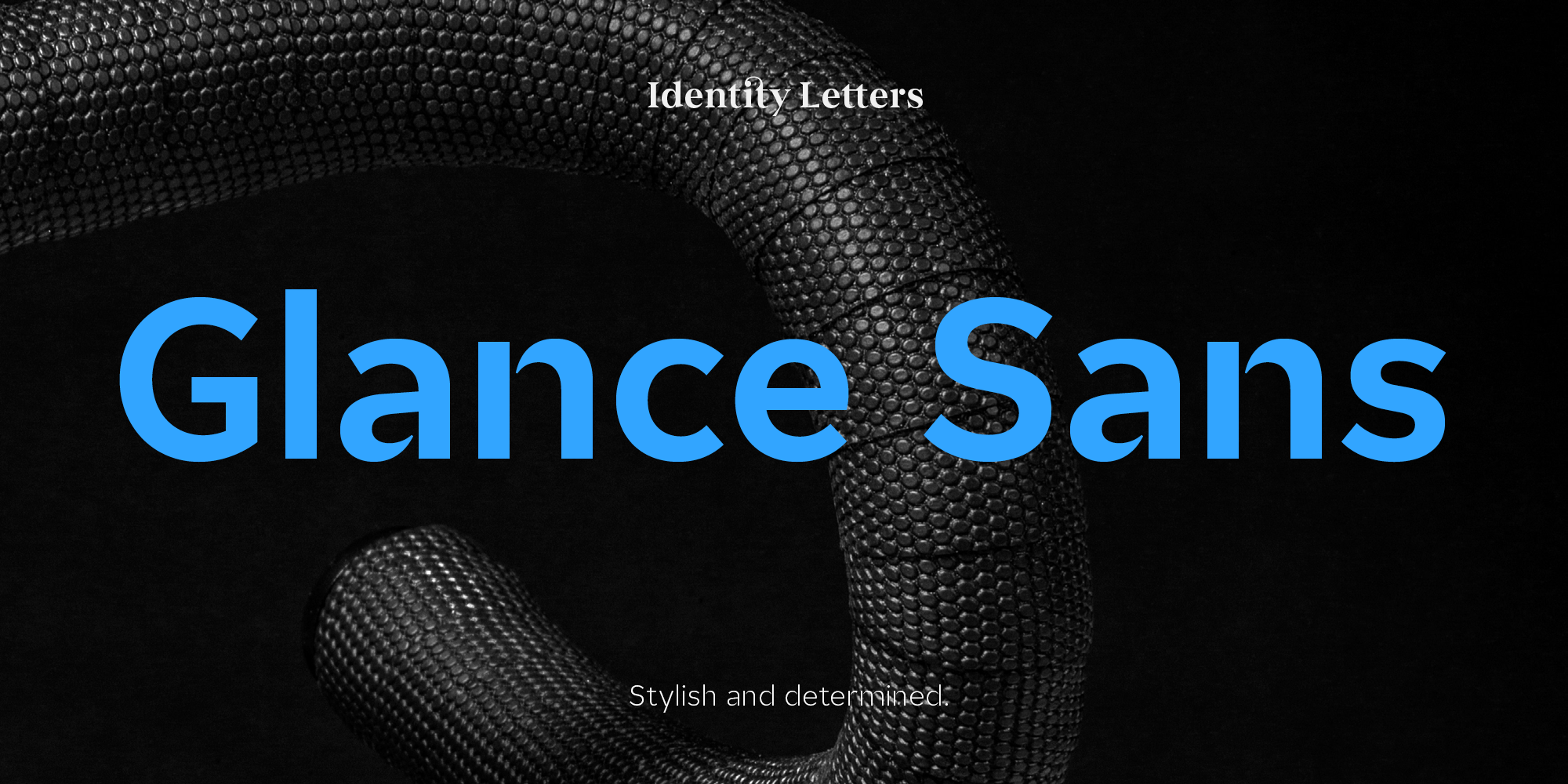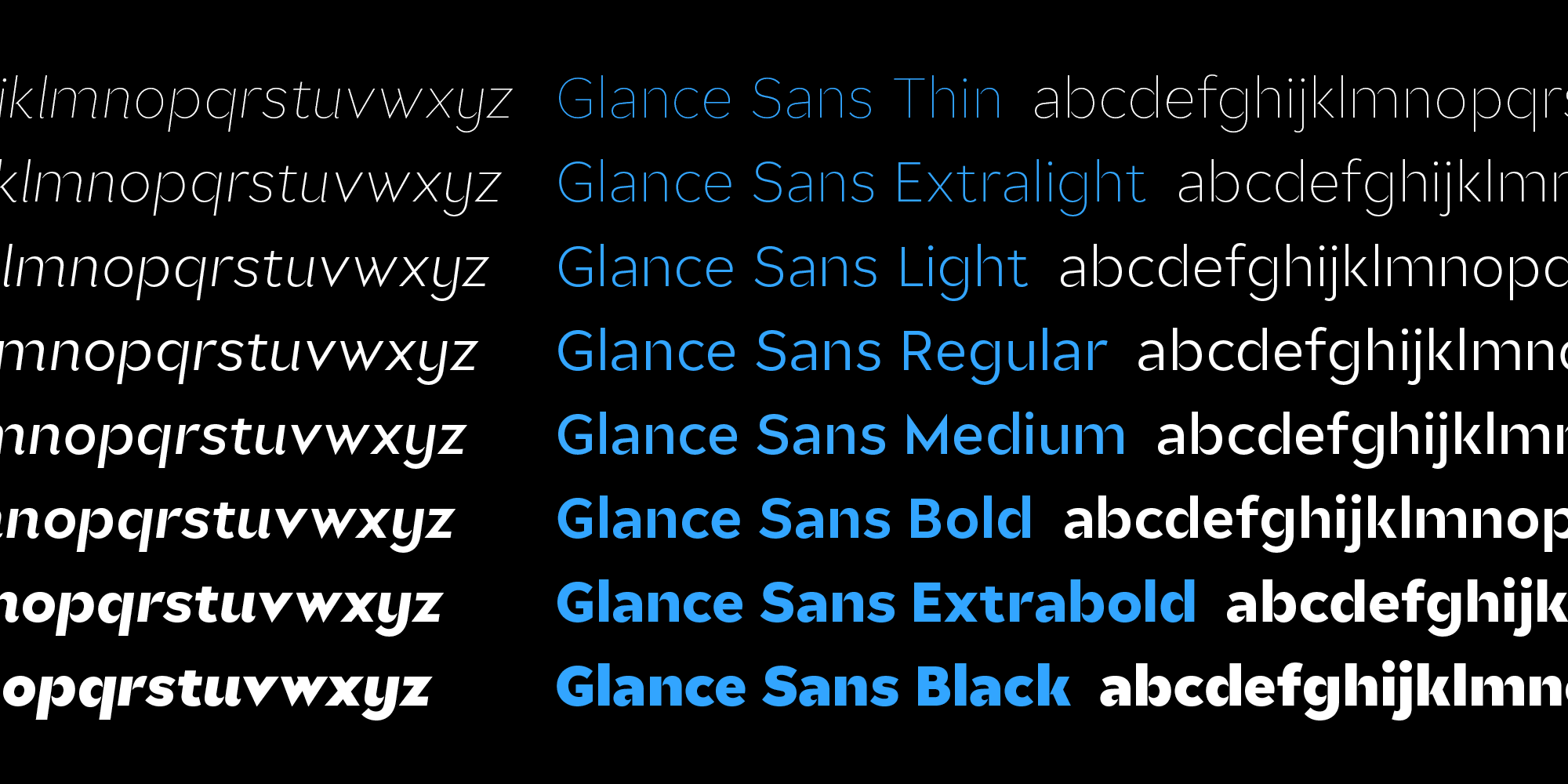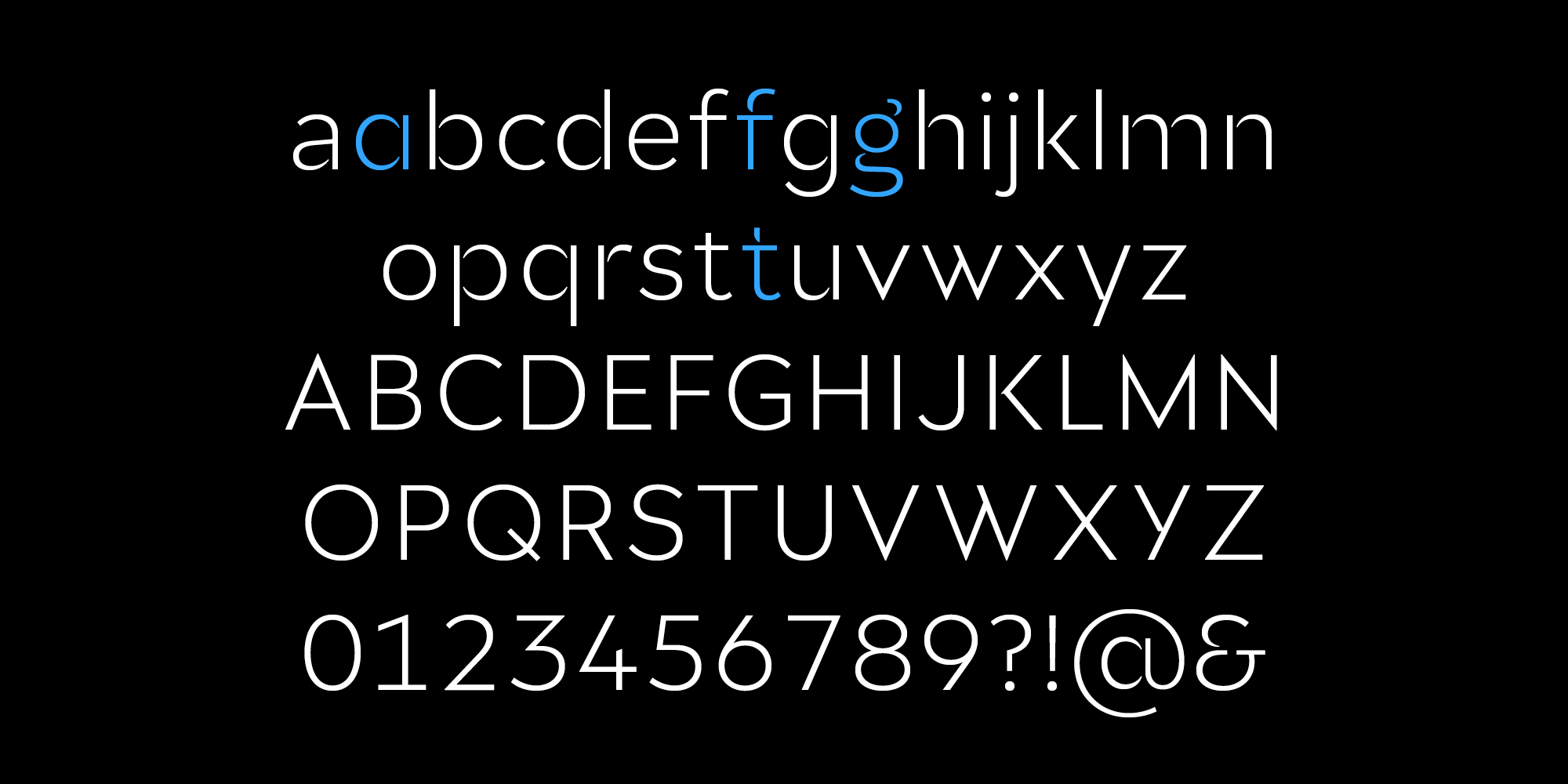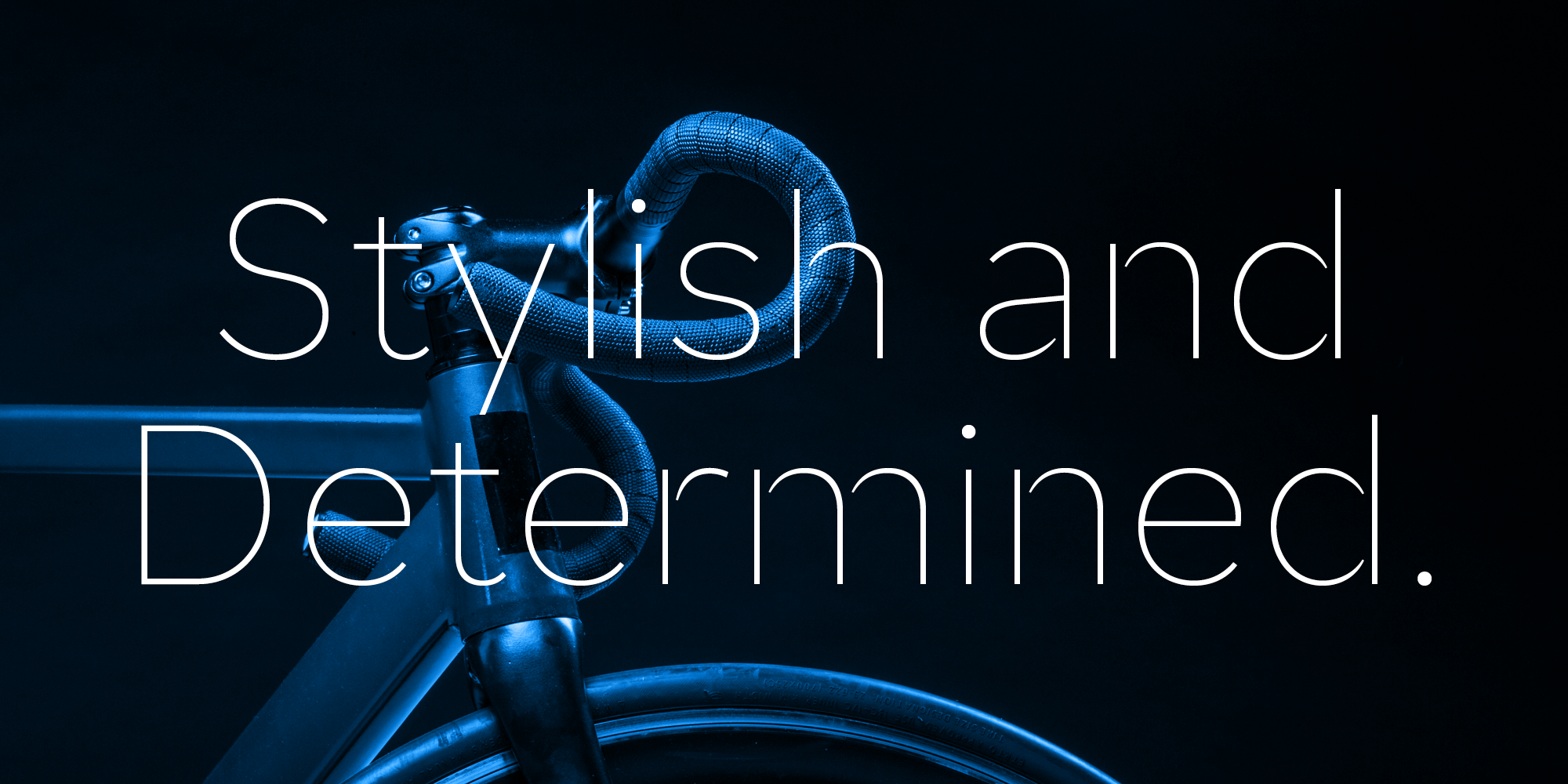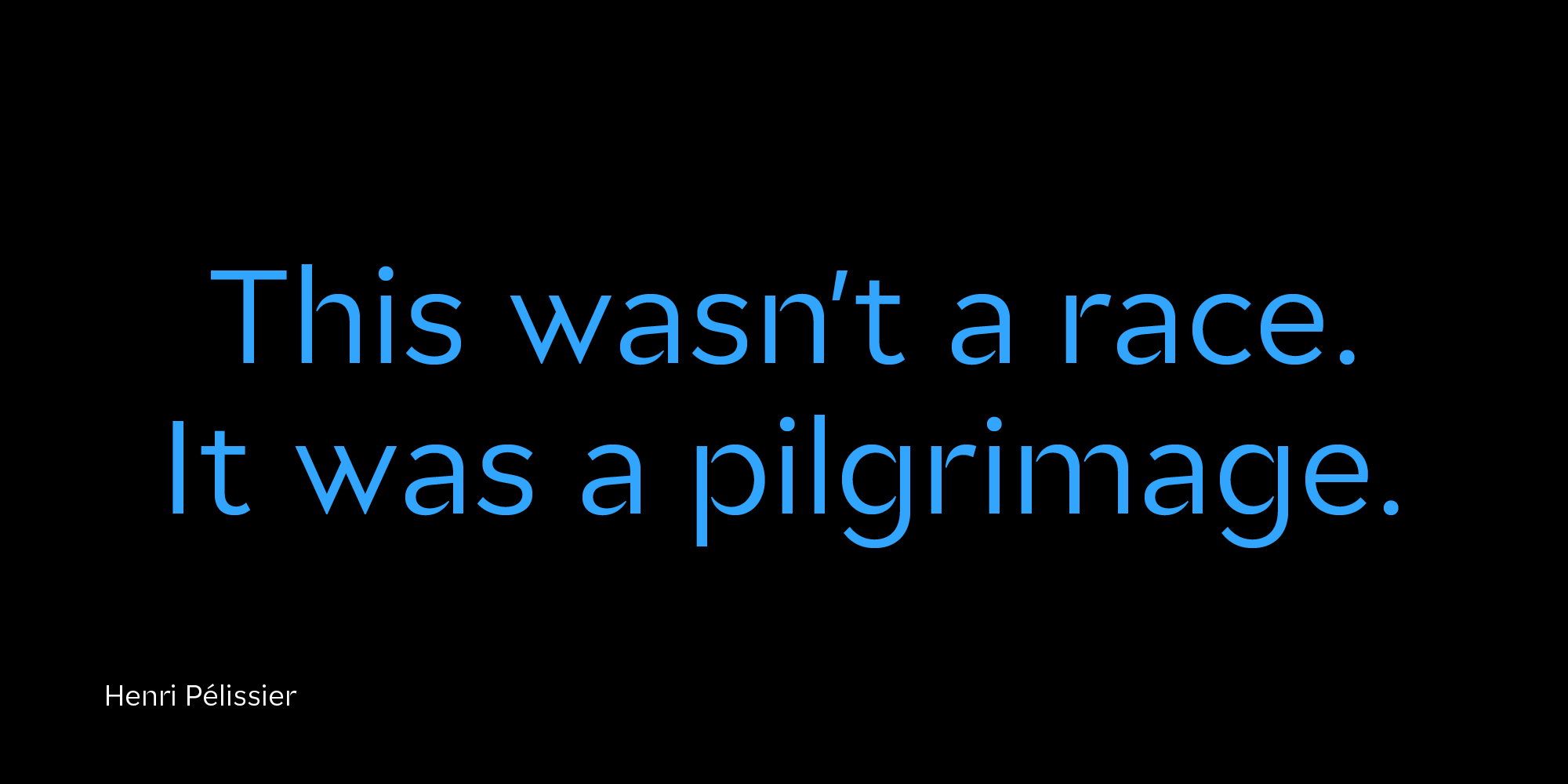
Im Jahr 2020 wurde Glance Sans von Moritz Kleinsorge gestaltet und in seiner Typefoundry Identity Letters veröffentlicht. Glance Sans folgt dem Gestaltungsprinzip der nicht verbundenen Elemente. Einige Striche verbinden sich nicht mit ihren Buchstabenstämmen, wodurch sichtbare Lücken entstehen.
Die Schrift besteht aus acht Strichstärken mit Kursiven. Unter den mehr als 650 Glyphen finden sich OpenType-Features wie sechs Ziffernsätze, eingekreiste Zahlen, eingekreiste Pfeile und zahlreiche Währungssymbole in zwei stilistischen Versionen.